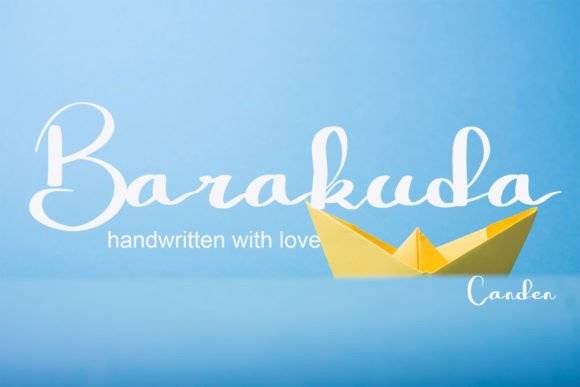
Fuente Barakuda para titulares, carteles y proyectos de marca
Fuente Barakuda
Barakuda es una fuente manuscrita creada con una tableta gráfica que ofrece una apariencia simple y natural. Perfecta para sitios web y publicidad , combina simplicidad con un estilo moderno y elegante.
- Escrito a mano con tableta digitalizadora
- Look simple y natural
- Ideal para sitios web y publicidad.
- Fresco y con estilo
A pesar de su simplicidad, la fuente Barakuda destaca por su encanto único.